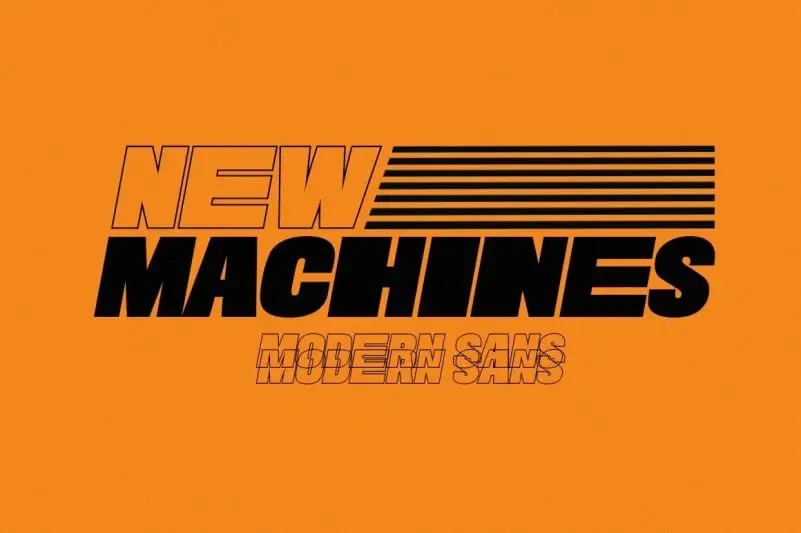
Introduzimos a New Machines Sans Serif Font – uma nova escolha para seus projetos visuais modernos e sofisticados. Esta elegante sans serif é especialmente concebida para destaque, com um estilo urbano que se destaca nos ambientes de design mais exigentes. Com seus gílias atualizadas e acessíveis, a New Machines Sans Serif Font traz facilidade ao acesso de elementos alternativos sem necessitar de conhecimentos técnicos. Instale-a em seu projeto e inicie sua criação. O comando Shift é suficiente para explorar os detalhes do design. Esta fonte abrange versões Regular e Outline, oferecendo um conjunto completo que atende tanto aos requisitos mais simples quanto aqueles exigentes por uma aparência sofisticada. Uma escolha moderna e conveniente para quem valoriza a eficiência na criação de projetos visuais.